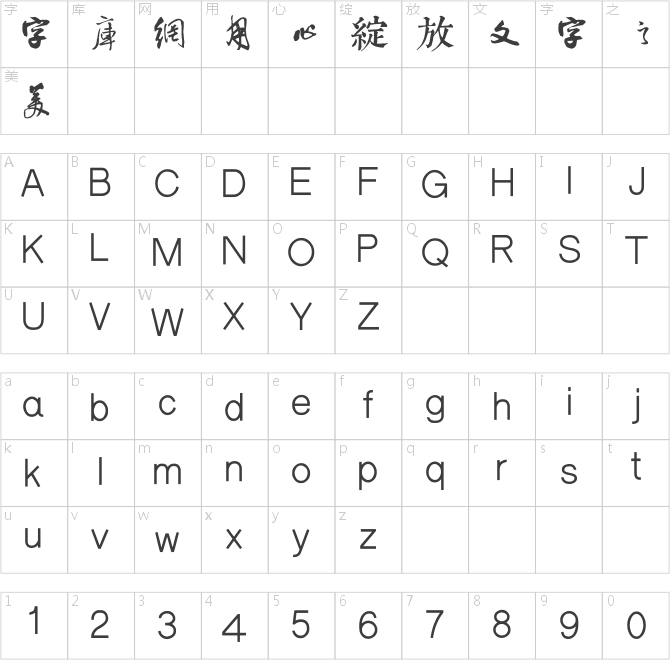
字体名称: 邯郸王铎千字文
邯郸王铎千字文
邯郸王铎千字文字体下载邯郸(清)王铎千字文
王铎(1592年—1652年),字觉斯,一字觉之,号十樵、嵩樵, 又号痴庵、痴仙道人,别署烟潭渔叟,河南孟津人  。明末清初书画家 。他的书法与董其昌齐名,有“南董北王”之称  。北京大学教授、引碑入草开创者的李志敏评价:“王铎的草书纵逸,放而不流,纵横郁勃,骨气深厚”。明天启二年(1622年)中进士,受考官袁可立提携,入翰林院庶吉士,累擢礼部尚书。崇祯十六年(1643年),王铎为东阁大学士。
崇祯十七年(清世祖顺治元年,1644年)满清入关后被授予礼部尚书、官弘文院学士,加太子少保。
清顺治九年(1652年)病逝故里。享年六十一岁,葬于河南巩义洛河边,谥文安。
王铎的书法作品有《拟山园帖》和《琅华馆帖》等,其绘画作品有《雪景竹石图》等。